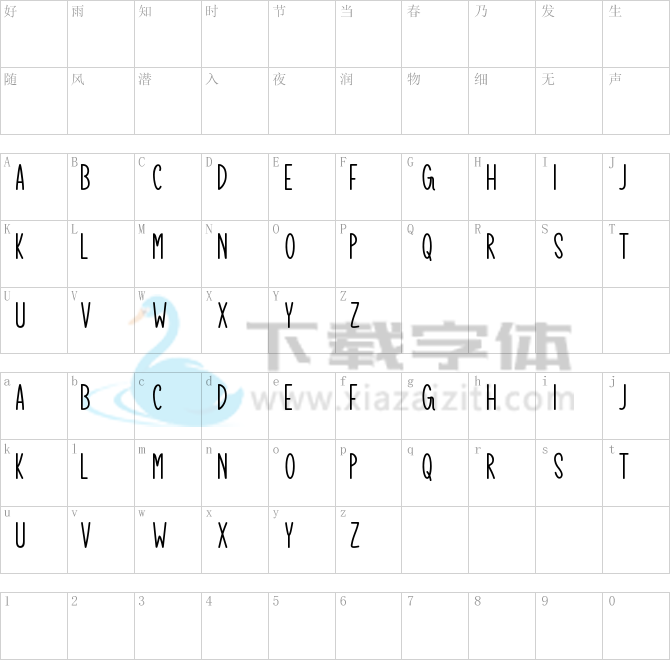
Autumn Arbor.otf字体下载,这款字体结构工整、笔画清晰,兼顾美观与易读性,适用于标题、正文、海报、包装、LOGO 等多种场景。字形优雅稳定,风格百搭耐看,适配日常排版与创意设计,让文字呈现更舒适、更具质感。Autumn Arbor.otf字体下载一笔一画,皆是细节,以均衡的比例、流畅的线条打造舒适视觉体验,字形端正大气,风格简约现代。无论是商业设计、品牌宣传还是日常排版,都能轻松驾驭,让文字更有格调与力量。Autumn Arbor.otf字体下载字体下载。
• 字体名称:Autumn Arbor